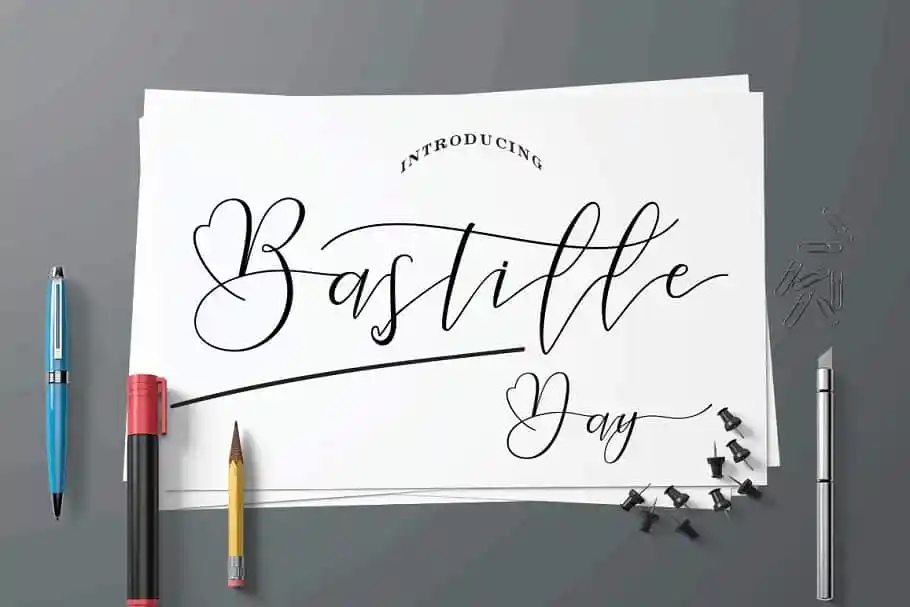
Bastille Day Script Font é uma elegante tipografia moderna criada pelo designer 24Design. Inspirada no estilo do Calligrafia Bastille Day, essa fonte foi desenvolvida a partir de escritas manuscritas reais, oferecendo formas únicas e modernas da calligrafia. Com linhas perfeitas e um toque feminino, ela se destaca como uma ótima escolha para aplicações variadas como moda, identidade corporativa, design gráfico e muito mais. Suas minúsculas, maiúsculas e múltiplas línguas a tornam versátil o suficiente para abarcar um amplo espectro de projetos, desde as etiquetas da sua próxima coleção até a identidade visual de seu novo negócio digital. Não hesite em experimentar essa fonte moderna e sofisticada que traz uma sensação natural ao seu projeto.